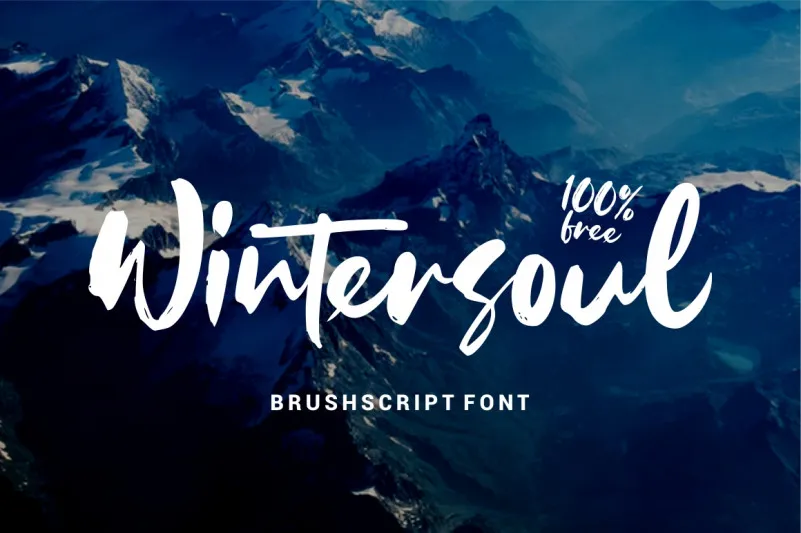
Wintersoul Brush Font – Fonte Grátis
Wintersoul Brush Font
A Wintersoul Brush Font é uma nova criação da Garisman Studio, lançada como uma opção script brush para designers de ambientes digitais criativos e sofisticados. Esta fonte apresenta um olhar elegante e refinado, com traços que são both atraentes e leves ao mesmo tempo. Idealmente projetada para dar um toque único às suas campanhas branding, esta é uma escolha ótima para aplicar em logotipos, convites, materiais de decoração, e até mesmo em publicações online como redes sociais ou postagens do Instagram, anúncios e embalagens de produtos. A Wintersoul Brush Font também oferece um design perfeito para criações fotográficas, marca d’agua, eventos especiais ou qualquer outro tipo de projeto visual. Se você busca uma fonte que possa tornar sua arte digital ainda mais elegante e personalizada, a Wintersoul Brush Font é definitivamente o caminho. Com suas linhas suaves e estilizadas, esta opção script brush se encaixa perfeitamente em um leque vasto de projetos visuais, garantindo tanto uma aparência sofisticada quanto criativa. Não importa do que seu projeto seja – se for uma marca empresarial, eventos sociais ou qualquer coisa no meio digital – a Wintersoul Brush Font pode ser o complemento ideal para dar sua arte um toque definitivamente único e memorável.